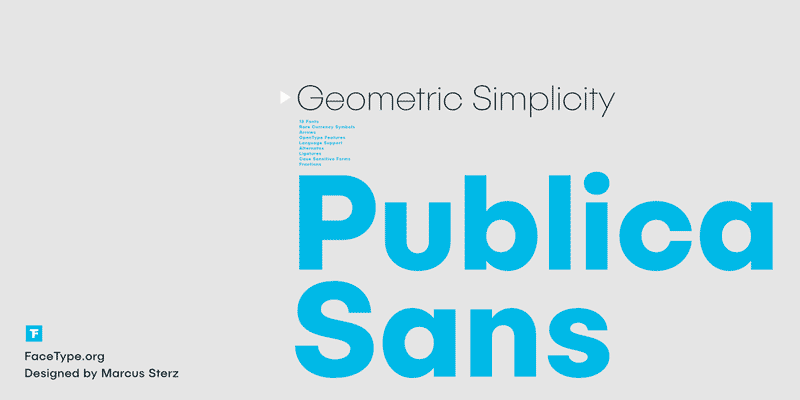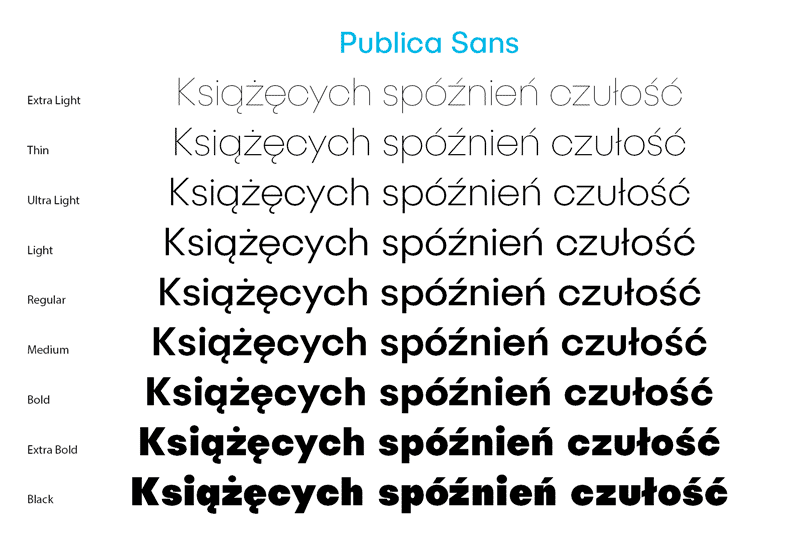
Font Publica Sans
Do naszego studia graficznego trafiła nowa rodzina geometrycznych fontów Public Sans. Zaprojektowana została w 2016 roku przez Marcusa Sterza. To nowoczesny i uniwersalny font mający 9 odmian wagowych wraz z italikami.